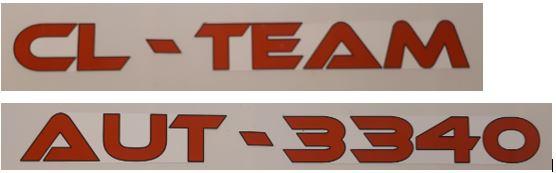
Kennt jemand diese Schrift? (CL-Team)
kennt jemand diese Schrift?
Der Klon wird den Designer Ray Larabie wahrscheinlich nicht erfreuen …
ffonts wird von ihm betrieben? Wusste ich nicht. Ich hätte auch nicht vermutet, dass er den Font gleichzeitg verschenkt (ffonts) und verkauft (myfonts et al.) Aber in der readme.txt bei ffonts ist er als Urheber genannt, dann wird’s schon passen :-)
Ray Larabie hat ja erst mit vielen, durchaus recht guten Freefonts angefangen, die teils deutlich aus dem oft Müll der damaligen Freefonts heraus ragte.
Später begann er, die besten dieser Freefonts teils komplett neu zu zeichnen, aber mindestens zu überarberiten, sowie komplette Familien daraus zu bauen und begann damit sein komerzielles Programm.
Diese Überarbeitung sieht man hier deutlich an den Ziffern.